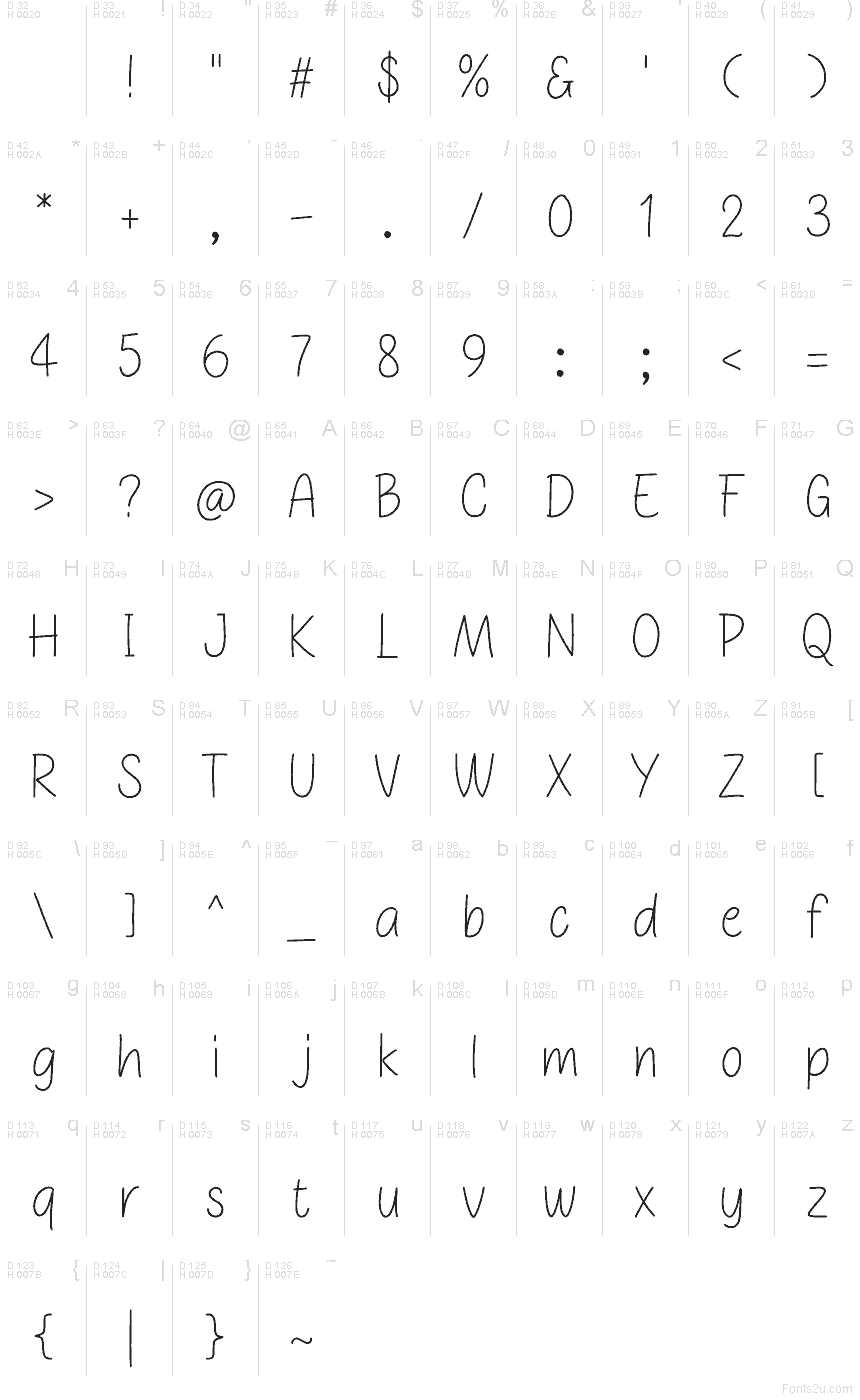
Tarusa Light
Шрифт Tarusa Light від Hello Good Studio — це безкоштовний рукописний шрифт із високими, вузькими штрихами та невимушеним, вільним ритмом. Його форми прості та відкриті, із закругленими закінченнями та легким малюнком, що надає йому природного, особистого характеру, без відчуття поспіху.
Tarusa Light чудово підходить для запрошень, вітальних листівок, цитат, логотипів та етикеток, оскільки його простий малюнок виглядає душевно і легко вписується в невеликі дизайнерські акценти. Цей безкоштовний шрифт також добре виглядає в заголовках блогів, на канцелярських товарах та в графіці для соціальних мереж, коли вам потрібен ефект рукописної нотатки, що залишається чистим і легко читабельним.